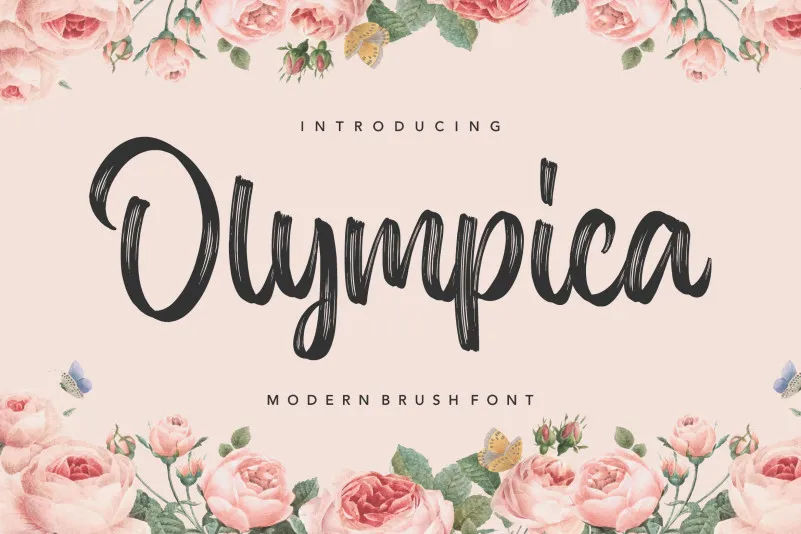
A fonte ‘Olympica Font’ é uma elegante caligrafia em estilo cursivo, perfeitamente adaptada para a criação de identidade visual e design editorial. Através de suas suaves curvas fluidas e delicadas, esta fonte cursive é ideal para criar um toque sofisticado e moderno nas marcações e logos. A característica mais marcante da ‘Olympica Font’ é sua textura cintilante, que adquire uma aparência vibrante e encantadora quando aplicada a projetos de branding fashion ou editoriais. Balpirick, o designer responsável por essa fonte, certamente teria muito orgulho ao vê-la usada para dar vida aos seus designs. Engane-se, se você ainda não tiver experimentado ‘Olympica Font’, é algo que vai adorar usar em seus trabalhos.